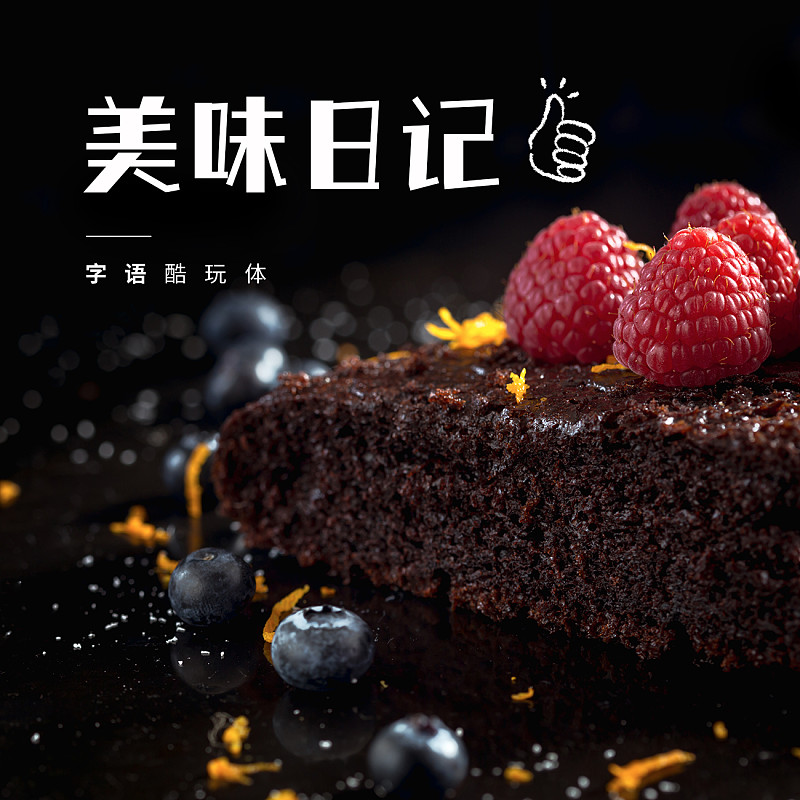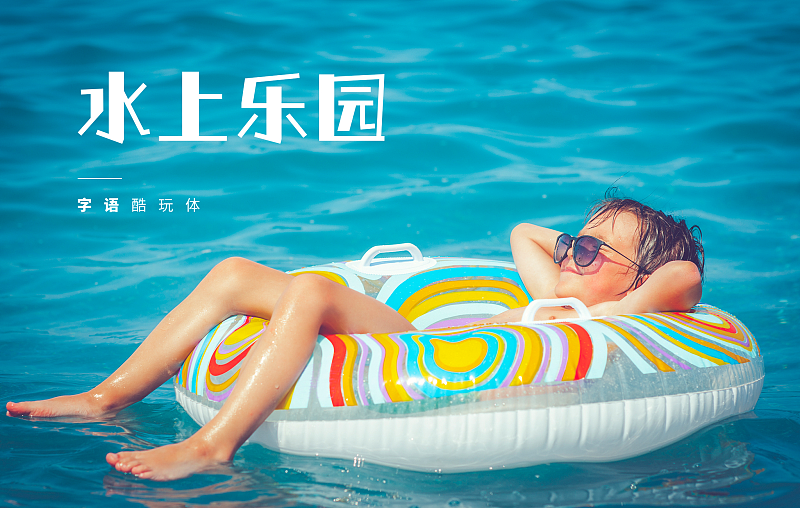
字語(yǔ)酷玩體
筆畫(huà)粗細(xì)對(duì)比明顯,變化多樣,視覺(jué)沖擊力強(qiáng);橫折分別傾斜,捺筆末端加入俏皮的“小尾巴”,使字體結(jié)構(gòu)達(dá)到一種微妙的平衡;風(fēng)格新穎,充滿趣味,是一款針對(duì)廣告,產(chǎn)品包裝,新媒體等設(shè)計(jì)的一款個(gè)性鮮明的創(chuàng)意字體,靈感來(lái)源于民國(guó)畫(huà)報(bào)字體設(shè)計(jì)